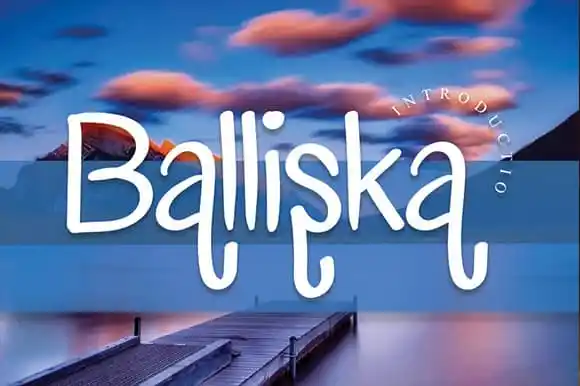
A fonte Balliska Handwriting é perfeita para quem procura uma escrita feita à mão com acabamento cuidadosamente elaborado. Desenvolvida pelo designer andikastudio, essa fonte adere-se a um estilo contemporâneo e elegante, ideal para estilos de projeto que exigem uma escrita autêntica e delicada. Seja para gráficos em mídias sociais ou peças promocionais, ou até mesmo para texturas de água e logotipos digitais – a Balliska Handwriting é uma opção indispensável. Suas linhas suaves e detalhes precisos permitem que ela seja utilizada em um vasto espectro de projetos, desde embalagens de produtos até as mais belas cartas devidamente organizadas. Com sua qualidade de escrita autêntica, a Balliska Handwriting é uma fonte indispensável para qualquer designer buscam incorporar um toque elegante e pessoal em seus trabalhos.